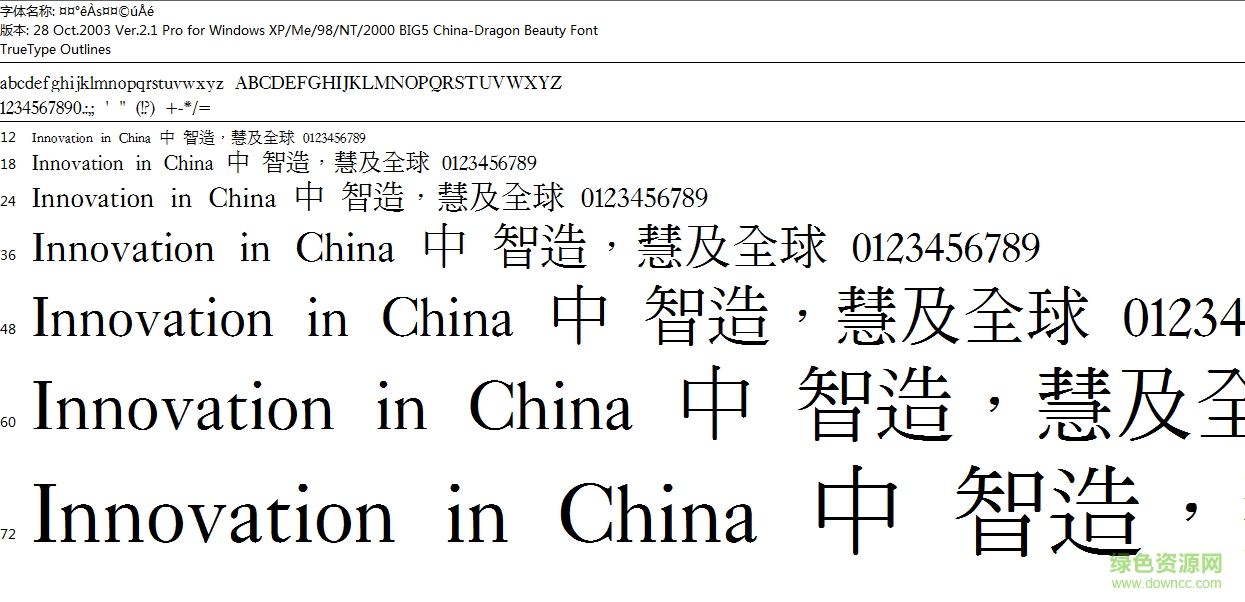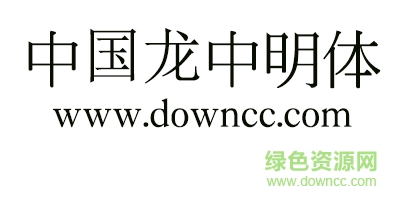
中國(guó)龍中明體字體能夠在多個(gè)行業(yè)領(lǐng)域進(jìn)行使用,如平面設(shè)計(jì)、印刷設(shè)計(jì)、商標(biāo)logo設(shè)計(jì)等等。這款字體設(shè)計(jì)的文字效果不僅美觀也很有特點(diǎn)!喜歡的網(wǎng)友快來(lái)綠色資源網(wǎng)下載吧。
中國(guó)龍中明體是一款非常漂亮的中國(guó)龍字體,這款字體字型整體形象簡(jiǎn)潔美觀,結(jié)構(gòu)對(duì)稱(chēng),下面有綠色資源網(wǎng)小編為大家提供免費(fèi)下載地址,有需要的朋友歡迎來(lái)下載使用!